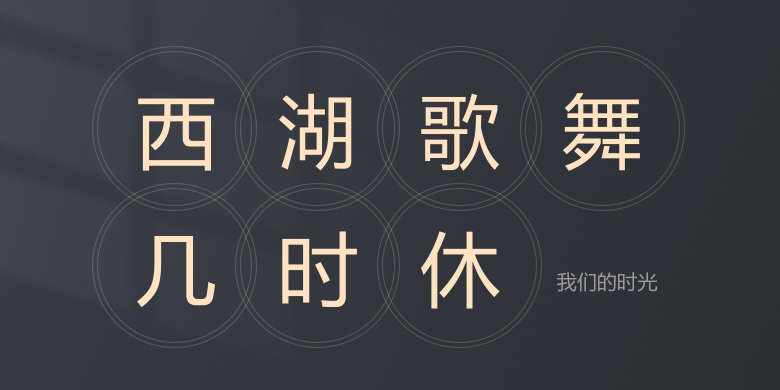
我们的时光
我们的时光,这款字体结构工整、笔画清晰,兼顾美观与易读性,适用于标题、正文、海报、包装、LOGO 等多种场景。字形优雅稳定,风格百搭耐看,适配日常排版与创意设计,让文字呈现更舒适、更具质感。我们的时光一笔一画,皆是细节,以均衡的比例、流畅的线条打造舒适视觉体验,字形端正大气,风格简约现代。无论是商业设计、品牌宣传还是日常排版,都能轻松驾驭,让文字更有格调与力量。我们的时光字体下载。